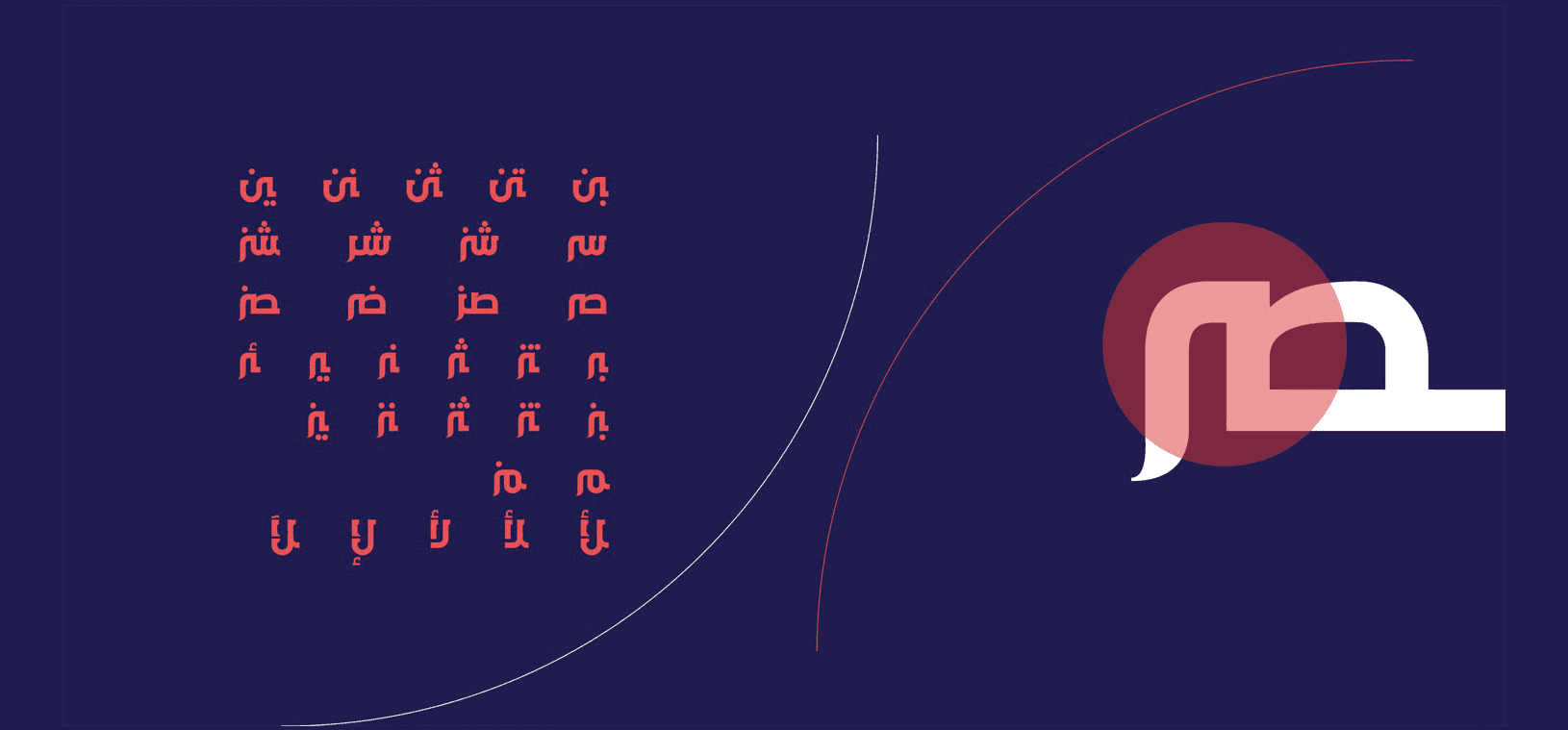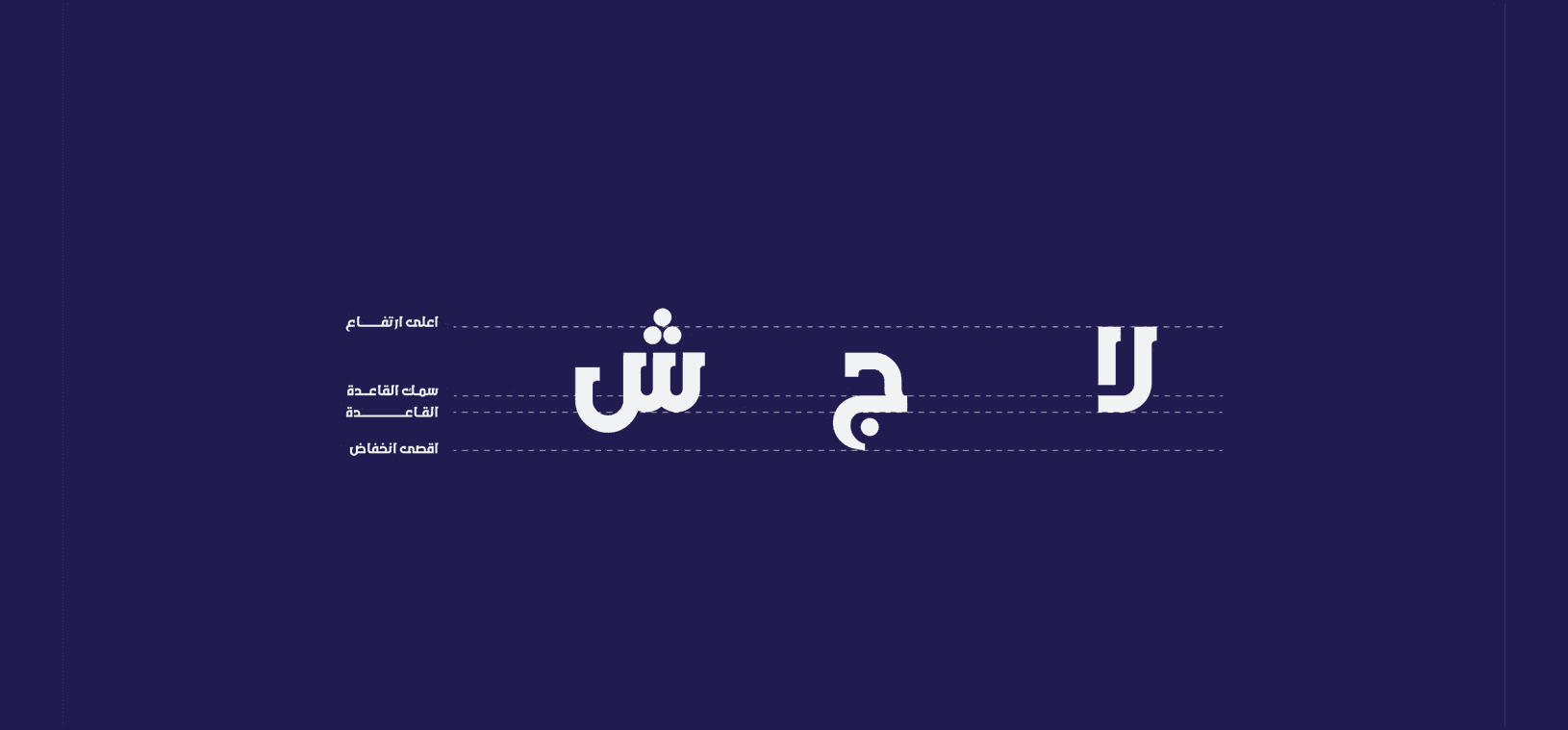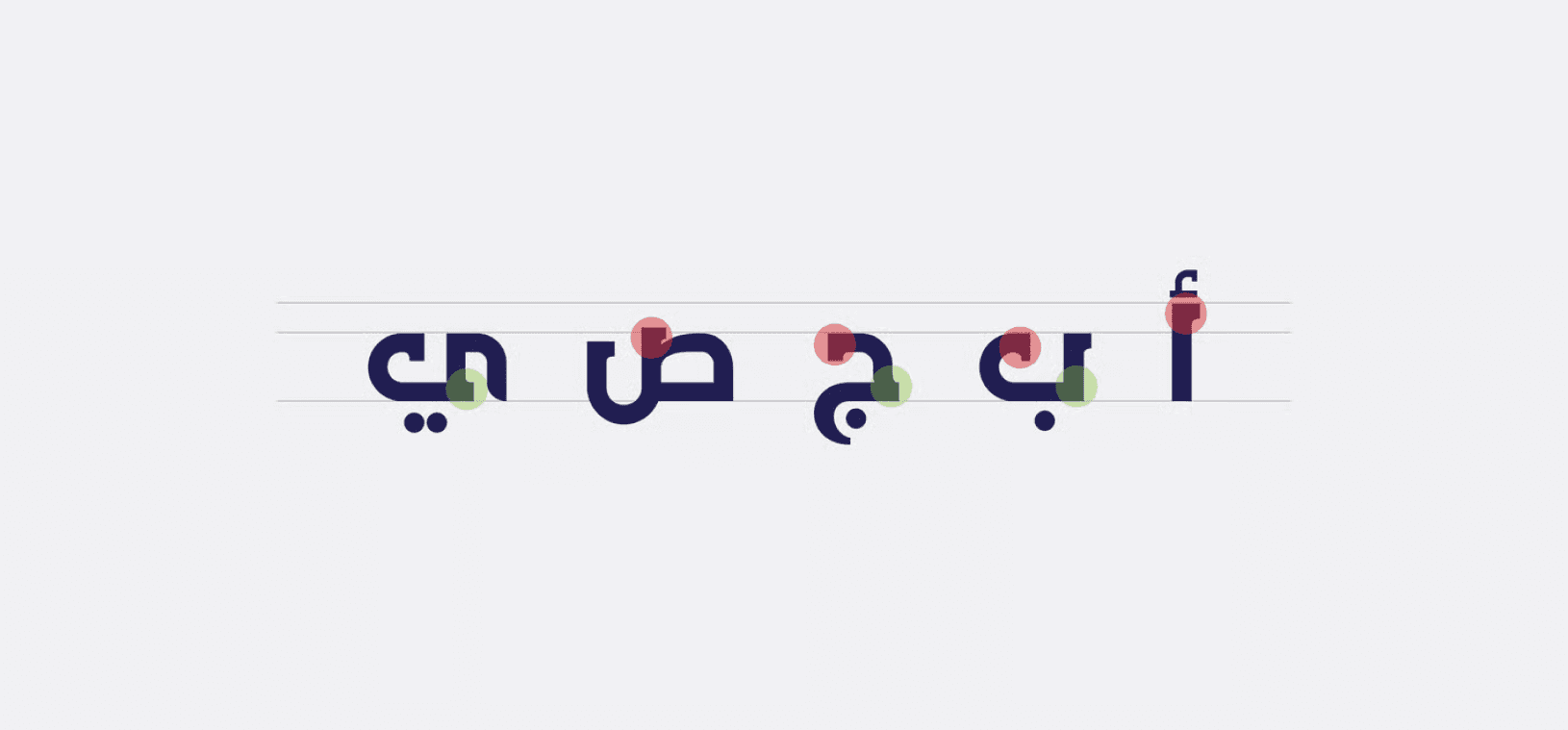
يُعد خط جيومتريك خيارًا مثاليًا للتصاميم الإعلانية التي تحتاج إلى حضور بصري قوي ومباشر. يتميز بتصميم هندسي عصري وحاد الحواف، ما يجعله مناسبًا للعناوين الجريئة والشعارات الحديثة. يأتي بوزن واحد "Bold" ليمنح النصوص وضوحًا وثباتًا في مختلف الاستخدامات الطباعية والرقمية. الخط عربي بالكامل ويوفر لمسة احترافية تلفت الانتباه في الحملات التسويقية والواجهات البصرية.